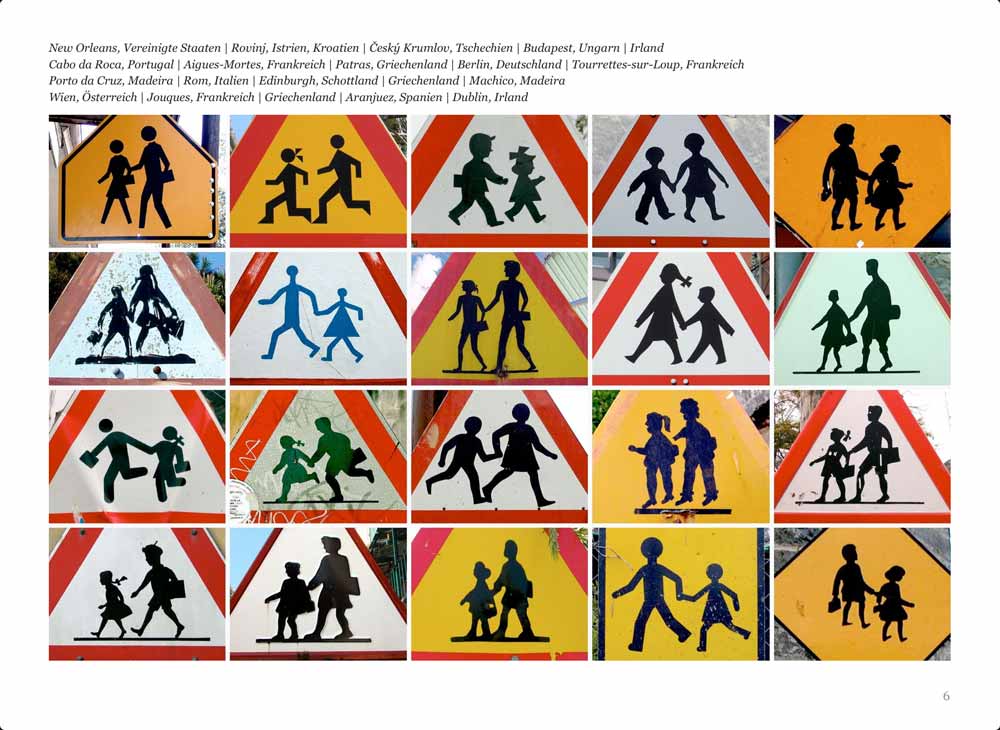
Vor drei Jahren erschien im Hermann-Schmidt-Verlag das Buch »Krieg der Zeichen – Spurenlese im urbanen Raum«, verfasst, fotografiert und gestaltet von Markus Hanzer. Ich habe das Buch damals ausführlich besprochen (Stadtgespräche: Spurenlese im urbanen Raum), es wurde kommentiert, viel gelobt (HD Schellnack: »Das Buch ist grandios.«), aber auch kritisiert. Letzteres mündete in die erste und einzige Leserkritik im Fontblog, verfasst von Fritz Grögel: Krieg der Zeichen — Eine Leserkritik. Sie beginnt: »Dieses Buch stinkt.« Die Verlegerin Karin Schmidt-Friederichs machte in einem Kommentar das Zusammenspiel von Biodruckfarben und Ökopapier dafür verantwortlich.
Zumindest das olfaktorische Problem ist jetzt gelöst: Krieg der Zeichen ist soeben als iBook für das iPad erschienen. Kostenlos und geruchlos! Auch inhaltlich hat Markus Hanzer sein Werk überarbeitet. Das technische Lesererlebnis ist durch die Ausnutzung der iBook-Möglichkeiten ein wahrer Genuss. Dazu gleich mehr.
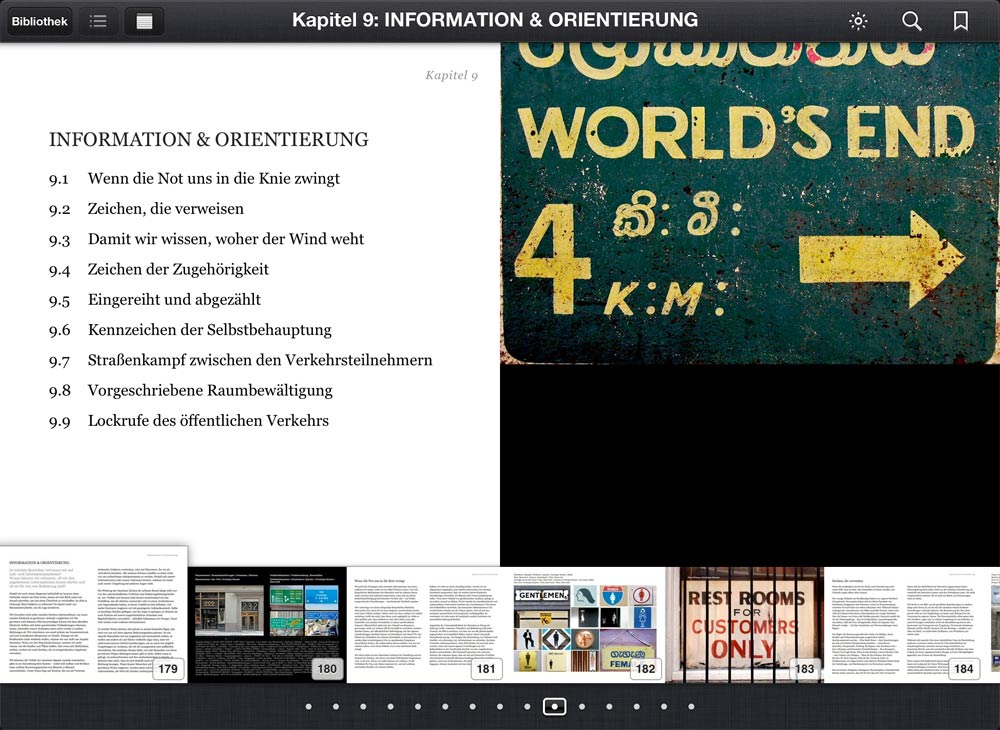
Hauptberuflich betreut der Wiener Designer und Markenentwickler Markus Hanzer große und kleine Medienunternehmen, darunter viele Fernsehanstalten. Von 2006 bis 2010 war er Partner bei der Markenagentur Mira4, seit 2011 ist Hanzer Partner von Qarante Brand Design. Darüber hinaus lehrt er an der FH Salzburg sowie an der Angewandten in Wien.
Privat treibt ihn seit Jahren eine große Leidenschaft an, nämlich Buchstaben und Schilder im öffentlichen Raum. Deswegen gründete Hanzer des virtuellen Typemuseum, aus dem sich später die Internetseite Stadtgespräche entwickelte, mit Fotografien aus dem öffentlichen Raum. Auf seinen Reisen liest er die vielfältige (typo)grafische Zeichen der Städte wie Romane. Seine Sammlung blickt auf die sichtbare Oberfläche unserer Umwelt und analysiert systematisch, welche Motive das Erscheinungsbild unserer Umwelt prägen. Welche Zeichen und Botschaften lassen wir in unser Bewusstsein dringen? Wie funktionieren die Selektionsmechanismen unserer Wahrnehmung? Welchen typografischen Formen messen wir Bedeutung zu? Woran orientieren wir uns?
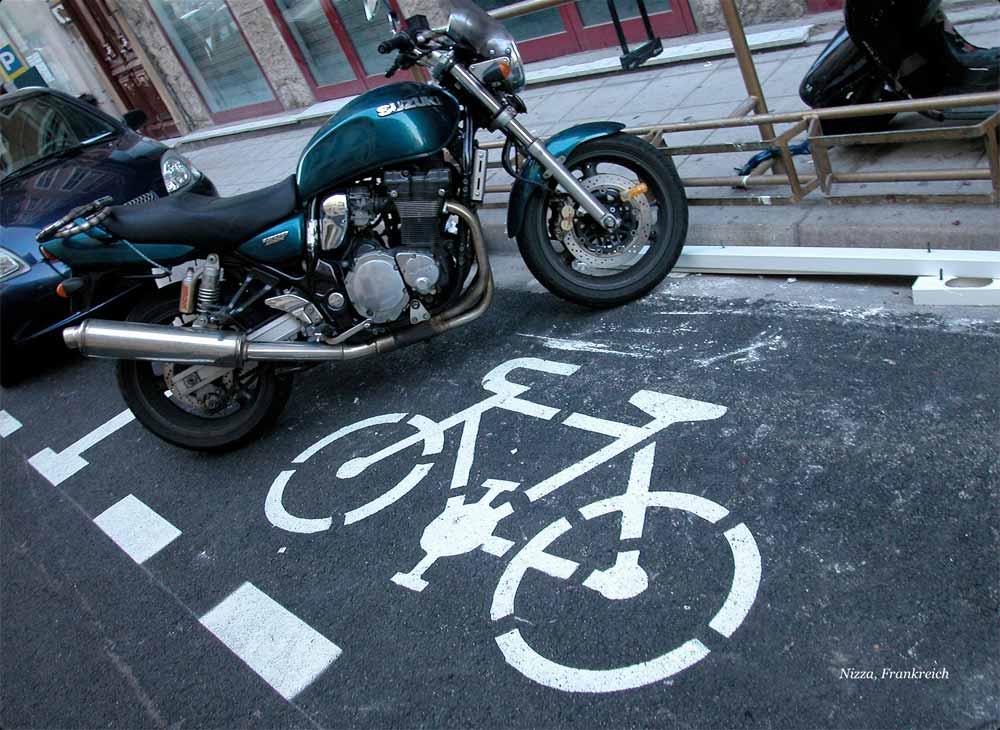
Nach vielen Jahren Sammeltätigkeit entstand vor 3 Jahren das gedruckte Buch zu den Stadtgesprächen, das eine Zwischenbilanz zieht. Und dies zu einer interessanten Zeit. Warum? Markus Hanzer verriet es mir in einem Gespräch: »Der öffentliche Raum stand noch nie so im Mittelpunkt wie heute. Durch die Zersplitterung der Medien Fernsehen und Zeitschriften entwickelte er sich zum einzig verbleibenden Gemeinsamen.« Die Menschen sprechen nicht mehr über Fernsehsendungen, die am Abend zuvor Millionen gesehen hatten. Die Zeitungen verlieren an Bedeutung, Plattenfirmen gelingt wahrscheinlich nie mehr ein weltweiter Megahit. Stattdessen gewinnen Konzerte neu an Bedeutung, Sportfans zeigen mit Fahnen und Bemalung, welche Mannschaft sie unterstützen, globale Konzerne inszenieren in den Großstädten haushohe Botschaften.
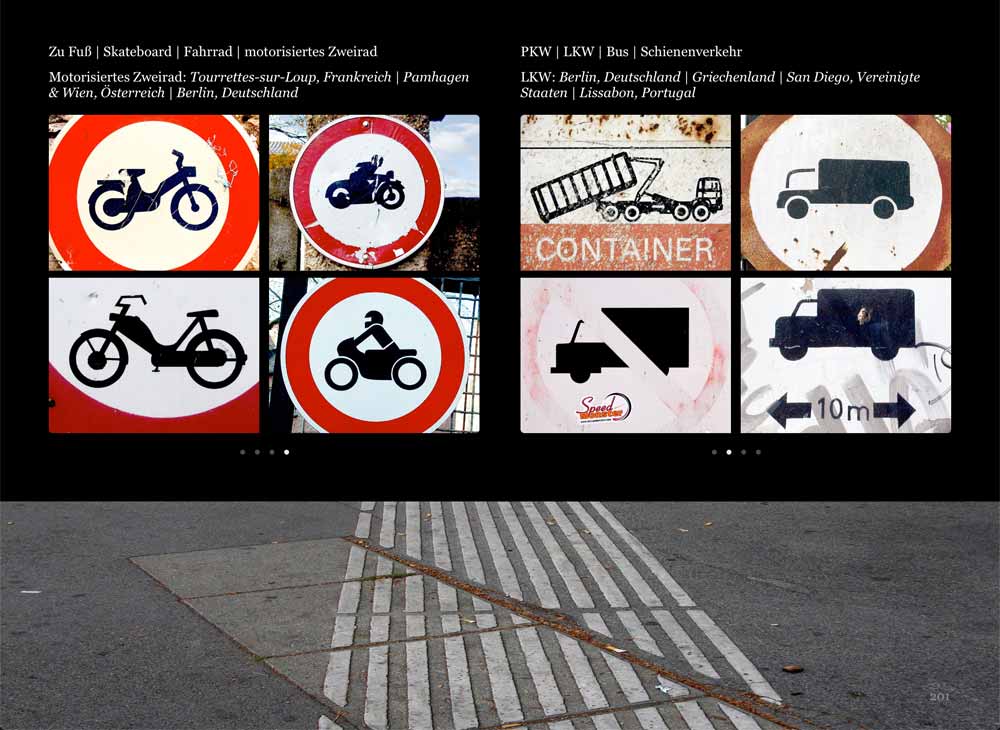
Doppelseite aus dem iBook »Krieg der Zeichen» von Markus Hanzer: Es macht viel Freude, durch die Bildergalerien zu wischen, Großansichten aufzurufen und Lesezeichen zu setzen
Durch die digitale Aufbereitung hat das Buch noch mal an Präsenz gewonnen. Auch wenn es (in diesem Fall: glücklicherweise) nicht mehr nach Buch riecht und beim Blättern keine Geräusche macht … die Bilder sind brillanter als je zuvor, lassen sich beliebig vergrößern, die Texte sind gut lesbar, interaktive Inhalte befeuern die Ausdauer beim Lesen. Die 12 Kapitel führen auch Laien leicht verständlich in die Welt der öffentlichen visuellen Navigation ein.
Harzers Buch liefert eine tiefsinnige Betrachtung zur Macht der Zeichen zwischen Information, Orientierung und dem Kampf um Kunden. Er verrät, wie sich urbane Kommunikation durch die Entwicklung der Medientechnik verändert. Wie man Aufmerksamkeit erzwingt. Was Formen verraten und wodurch Zeichen Macht ausüben. Wann und wie visuelle Kommunikation Reviere absteckt und aus der Masse heraussticht. Wie Zeichen trotz Reizüberflutung Orientierung geben und welche Bedeutung Zeichen für unterschiedliche Formen gesellschaftlichen Zusammenlebens haben. Viel Spaß beim Lesen. [Update … hier geht's zum Hanzer-Buch im iBook-Store]
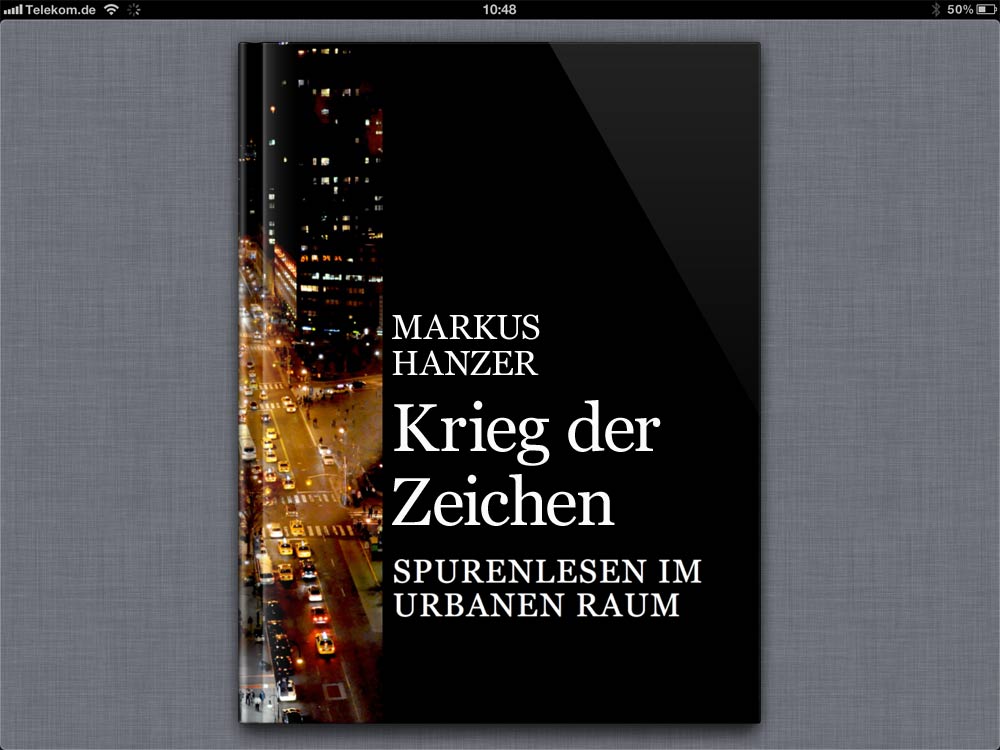
Das erste Foto ganz oben ist verlinkt. Aber Du hast recht, danke für den Link.
Danke für den Tipp!
Bestimmt nett. Zugang hat leider in letzter Zeit immer öfter nur der, der das Eintrittsgeld an Apple abgetreten hat. Wenn das die Zukunft des Buchs ist, seh ich längerfristig schwarz für den gleichberechtigten Zugang zu Wissen und Information.